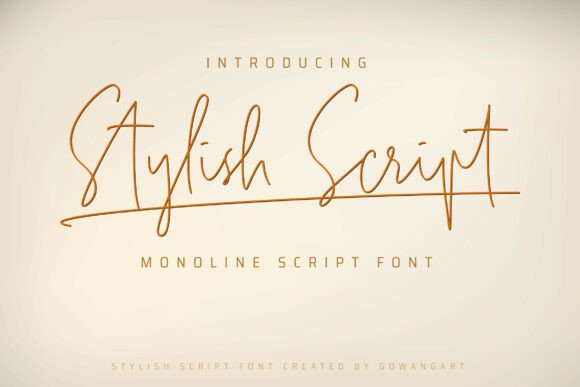
Stylish Script
Якщо ви шукаєте високоякісні ресурси, такі як Stylish Script, цей преміум-пакет є фантастичним вибором для ваших творчих проектів.
Незалежно від того, чи створюєте ви продукти POD (друк на вимогу), весільні запрошення або графіку для соціальних мереж, Stylish Script стане ідеальним вибором.